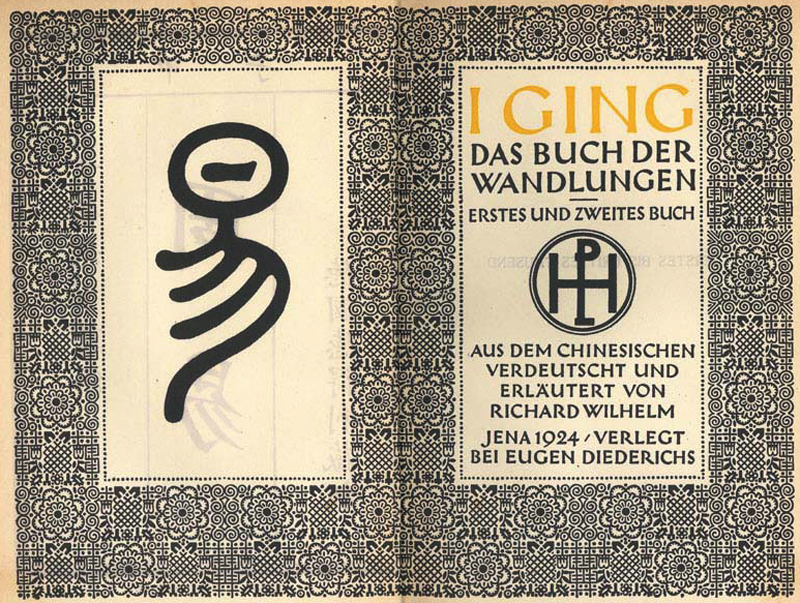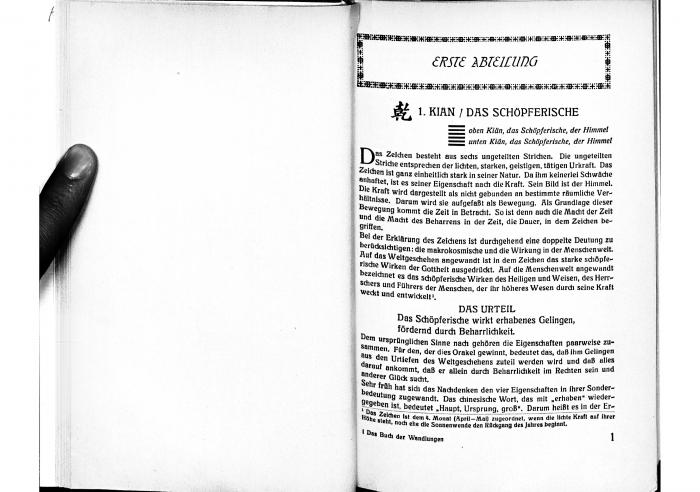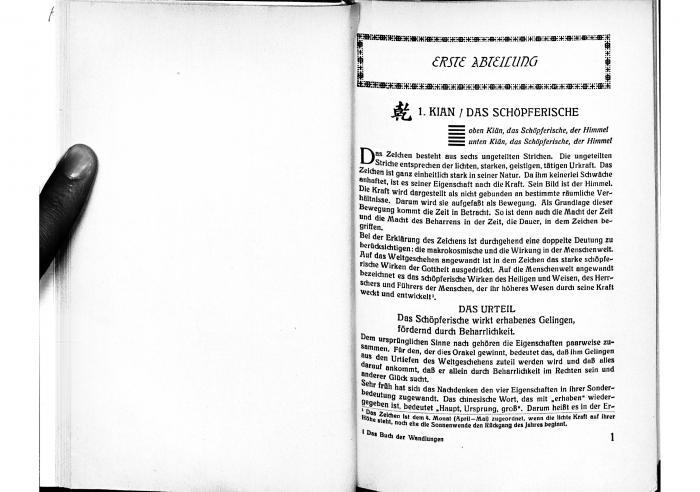
ich suche diese Schrift:
Hier noch eine Vergrößerung:
Der Scan stammt aus der Erstausgabe des Buchs »I Ging – Das Buch der Wandlungen« von 1924. Gestaltet wurde das Buch wahrscheinlich von Ernst Schneidler (zumindest beim Titel bin ich mir sicher).
Ich kann mir nicht vorstellen, daß die gezeigte Buchseite von Schneidler entworfen wurde. Seinem Regelwerk scheint das für mein Gefühl gar nicht zu entsprechen. Ich kann mich irren, aber ich würde wetten, daß diese Seite nicht von Schneidler stammt.
Die Satzschrift ist eine der vielen sogenannten Römischen Antiqua, die von 1900 an entstanden und in jeder Schriftgießerei mehr oder weniger modisch zu haben waren und von denen die Leser nach einigen Jahrzehnten wieder erlöst wurden. Könnte die Neue Römische Antiqua von Berthold sein.
Hier der Titel ein bisschen weniger verzerrt:
Die Umrandung entspringt dem Mong Dsi:
Ob der Inhalt in der selben Schrift gesetzt ist, wage ich nicht zu beurteilen.